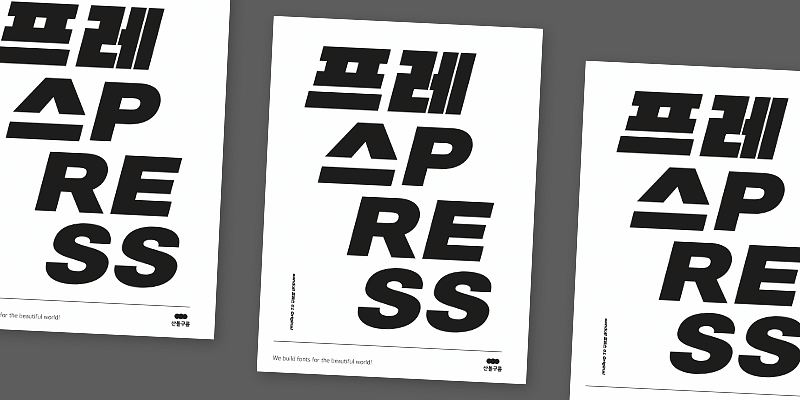
Sandoll Press est le quatrième produit du projet de miroir générationnel, reflétant la sensation d’accélération de la production non-stop et du rythme effréné de la culture populaire. Les caractéristiques de cette police sont les traits lourds et pleins avec la police composée Moim, les lettres larges et basses, ainsi que l’inclinaison pour invoquer l’image des vitesses élevées de la production de masse.